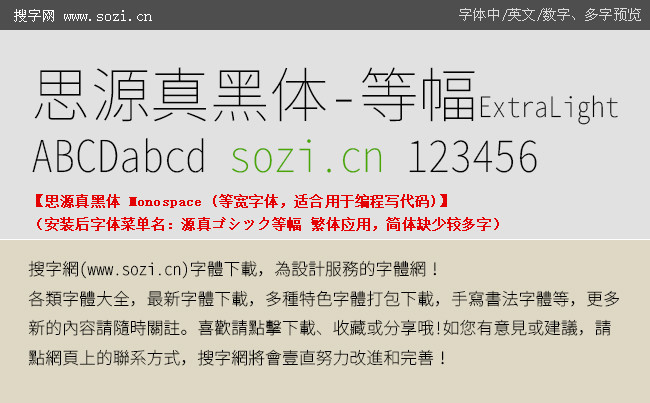
思源真黑體-等幅ExtraLight
搜字網(wǎng)給大家提供一款思源真黑體-等幅ExtraLight中文字體下載,思源真黑體字體是源于Google的開源字體思源黑體,保留了思源黑體原版的優(yōu)雅以及高可讀性的特色,并在思源黑體的基礎(chǔ)上做出了變化,使得整套字體看起來更加銳利清晰。等寬字體 GenJyuuGothic - Monospace適合用于編程寫代碼。